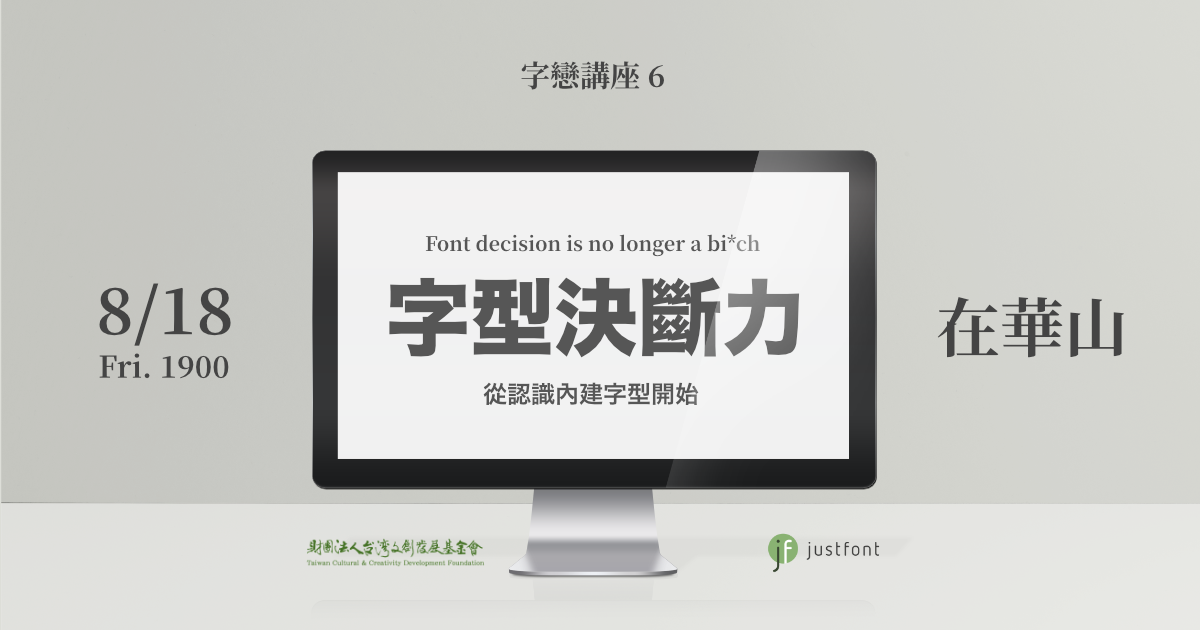
字戀講座是
由 justfont 主辦、籌劃的全新免費字型講座,
除了希望能推廣字型相關知識外,
也希望讓大家更深入瞭解字型設計的文化、歷史、技術、哲學⋯⋯
每次講座前半場,都會帶給大家台灣民眾必修的基本的字型知識,
也會在後半場依照時事、互動調查需求來規劃有趣的次領域主題,
希望能用輕鬆好玩的方式,讓大家更親近這個與我們息息相關的領域。
「電腦裡面好多字型喔!」「so? 沒幾個認識的啊~用來用去都那幾個」「額~如果我們挑幾個厲害的介紹呢」「安安你字型系?」
【#字戀講座:justfont 主辦的字型知識講座(免費參加)】
第六場:字型決斷力從認識內建字型開始
(aka Font decision is no longer a bi*ch)
字型是一種工具。電腦內建的字體選單,就是一個工具箱。
很多工具,看起來很厲害。但你曉得這些工具該如何使用嗎?
讓 justfont 的設計師們帶你認識這些:
你花了錢跟電腦一起買(但你可能不知道
擺在電腦裡面(但你可能沒用過
存在感很低(你可能沒聽過
但事實上很有故事也派得上用場的字型。
字型認識多了,決斷力也變強了!
這一場要談:
- 各平台經典的歐文、中文內建字型介紹
- 如何使用這些內建字型?版權怎麼辦?
難度:★☆☆ 歡迎有興趣的初學者